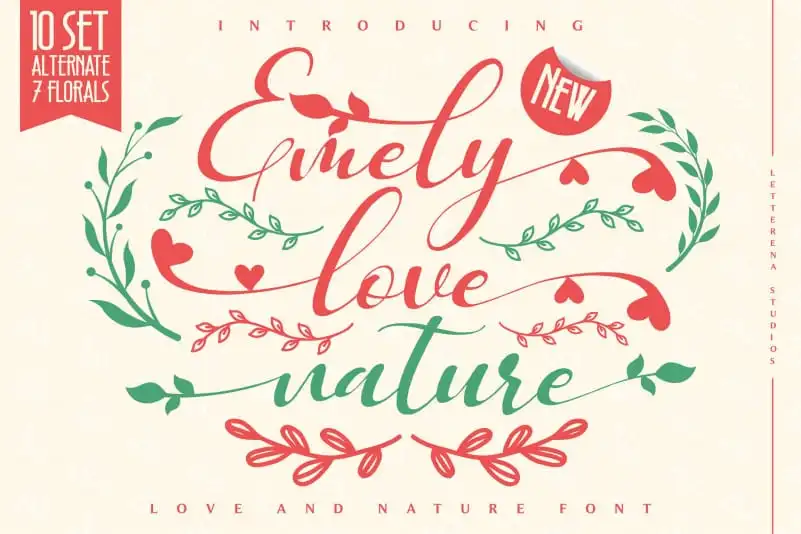
Emely love nature Calligraphy Font – Download Grátis
A Emely Love Nature Calligraphy Font é uma elegante fonte de escrita cursiva ideal para projetos que valorizam a natureza e um ar romântico. Inspirada na autenticidade do estilo à mão, esta fonte apresenta traços finamente equilibrados, variando em densidade e espessura, criando um aspecto suave e fluido. A PUA Encoding permite que você navegue facilmente entre todos os caracteres e adoráveis traçados da fonte. Seu design romântico e natural foi projetado para destacar o encanto de seus projetos. Sua delicadeza faz a Emely Love Nature uma escolha perfeita para designers apaixonados por arte escrita que desejam incorporar elementos naturais em suas criações.